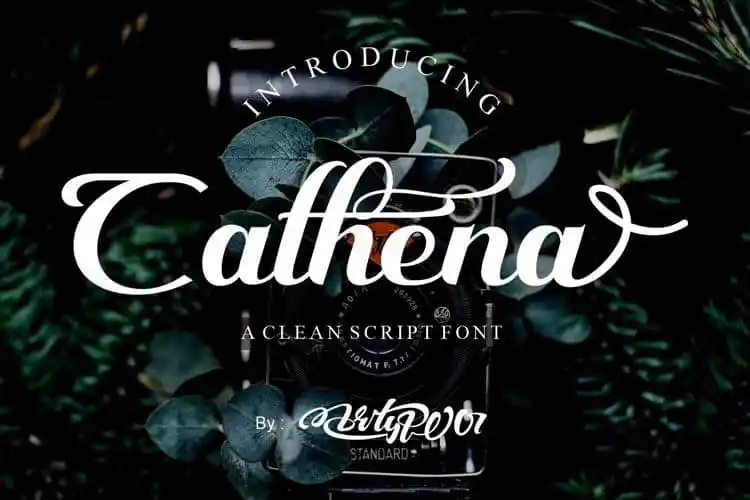
Introduzimos a “Cathena Script Font”, uma elegante fonte de script com um olhar refinado. Artype07 é quem criou e compartilhou esta fonte moderna, marcada por toques suaves e curvas belas em cada letra. Cathena destaca-se pela sua natureza bold, autoritária, luxuosa, moderna e premium. Para aqueles que desejam criar belos headlines ou textos para exibição, o recurso OpenType oferece alternativas de letras únicas, tornando a fonte ainda mais versátil e interessante. Cathena Script é uma escolha ideal tanto para designers como para quem busca um toque especial em seu trabalho visual. Descubra por si mesmo os inúmeros usos desta fonte única, que se destaca pela sua elegância discreta e sofisticação.